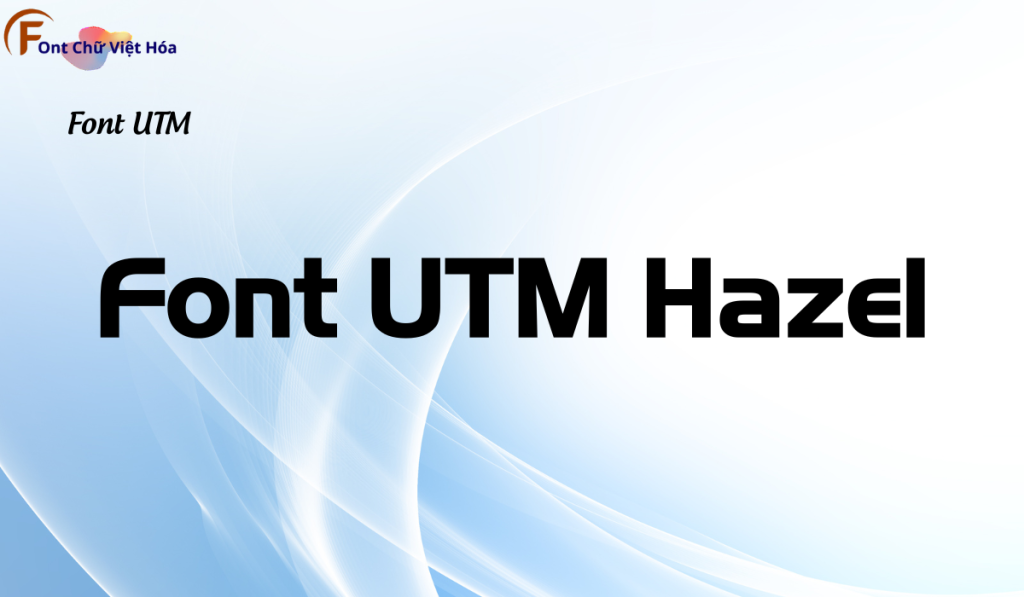
Font UTM Hanzel Việt Hóa
Tác giả: UTM Hanzel
Bộ Font: UTM
Phân loại: Cá tính, Độc đáo
Kiểu chữ: Có chân
Font UTM Hanzel Việt Hóa là một font chữ không chân hiện đại, thuộc bộ font UTM. Được thiết kế với mục tiêu mang lại sự đơn giản và hiệu quả, font này lý tưởng cho các dự án thiết kế như giao diện người dùng, ứng dụng di động, và website. Với các nét chữ rõ ràng và độ dày đều đặn, Font UTM Hanzel Việt Hóa không chỉ dễ đọc mà còn tạo cảm giác hiện đại và chuyên nghiệp. Việc Việt hóa font giúp người dùng dễ dàng tích hợp vào các thiết kế tiếng Việt, mang lại sự tiện lợi và nâng cao tính thẩm mỹ.